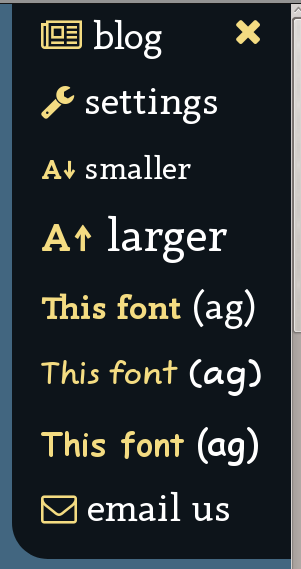
Gut lesbare Webschriften
Hallo, gibt es irgendwo einen guten Artikel über die Lesbarkeit von Webschriften?
Leider hat man ja nicht alle auf dem Markt existierenden Bildschirme und Geräte zum Testen zu Hause.
Ich gestalte gerade die Webseite für eine Organisation für neurologisch Erkrankte (mache sonst nur Print). Open Sans wäre jetzt meine Wahl. Source Sans sah z. B. auf einem niedrig-auflösenden Monitor grauenhaft aus ...
Ist dieser kleine Schalter zum benuzerdefinierten Einstellen der Schriftgröße eigentlich noch zu empfehlen (-> A+ | A-), oder ist sowas inzwischen out?
Wenn Leserlichkeit das Hauptkriterium ist (statt, sagen wir mal, die möglichst stringente Einhaltung eines CD/CI) würde ich überhaupt davon abraten, dem Leser eine Webschrift (ohne einfache Wechselmöglichkeit) aufzuzwingen. Warum? Weil eine Systemschrift seines Systems mit einiger Wahrscheinlichkeit besser leserlich ist (weil eben auf sein System optimiert) als irgendein Webfont.
Was macht ein Smartphonebesitzer denn als erstes? Richtig: eine Schrift aussuchen, die ihm gefällt/die er auf diesem Gerät gut lesen kann.
Webschriften sind ein nettes Extra, aber ich würde sie für besonders sensible Gruppen, was Leserlichkeit angeht, immer nur als Option anbieten. Ich habe in letzter Zeit einiges für Grundschüler gestaltet – in enger Abstimmung mit ihren Lehrern – und da auch mehrere Schriftoptionen angeboten. Das kann sinnvoll und hilfreich sein, weil Systemschriften eben nicht immer optimale Leserlichkeit für besonders sensible Gruppen von Lesern (wie eben Leselernanfänger, Dyslexiker,  Einwanderer, die gerade erst Sprache und Alphabet lernen, Menschen mit allerlei Behinderungen und und und) bieten. Serifenschriften können da helfen, wie auch komplexe a- und g-Formen (die weniger leicht mit o und 9 verwechselt werden) oder besonders humanistisch/»organisch« gestaltete Schriften, bei denen sich b, d, p und q besonders klar voneinander unterscheiden (auch wenn sie gedreht und gespiegelt werden).
Aber auf manchen Geräten sieht dann auch die sorgfältigst getestete Schrift eben nicht so klar aus wie eine Systemschrift. Deshalb: Wahlmöglichkeit!
Schon innerhalb eines Schulbezirks gibt es aber die unterschiedlichsten Geräte, auf denen Schriften ganz unterschiedlich dargestellt werden: ältere PCs, neue PCs, Chromebooks, »richtige« Laptops, Tablets verschiedenerer Generationen, Telefone, Smartboards (auf denen Schriften dann ganz anders wirken als auf dem angeschlossenen PC) . Da ist der Testaufwand schon bei einem Nutzer, den man kennt, enorm. Wenn der Leser irgendjemand sein kann, nun ja …
Nach meinen Erfahrungen ist er (wenn Erwägungen wie die obigen wichtig sind) wichtiger denn je, da eben immer mehr Inhalte auf nichttraditionellen Geräten konsumiert werden. In einem PC-/Laptop-Browser kann ich selbst als naiver Nutzer die Schriftgröße ziemlich einfach anpassen, ohne das Layout zu zerschießen. Ctrl-+ gedrückt oder auf das + in der Browserleiste geklickt, schon ist die Schrift größer! Aber schon auf einem Smartphone ist das klar schwieriger. Klar, da kann ich pinch-zoomen, aber dann passt eben eine Textzeile nicht mehr in den Viewport. Doof! Da kann eine A+ A- Option sehr helfen.
Sehr guter Text, Thorsten! Was man vielleicht auch noch mit einbeziehen könne ist, das viele Browser inzwischen ja einen „Lese-Modus“ haben in dem dann nur der Text der Seite unabhängig vom Seiten-CSS angezeigt wird. Man sollte die Seite auslösen auch so gestalten, das dieser Modus zuverlässig funktioniert.
Und vielleicht wäre es auch schlau, einen Dark-Mode anzubieten.
Schriften würde ich auch nicht fest vorgeben, die Nutzer wissen besser, was ihnen hilft. Ansonsten ist noch eine klare, einfache Gliederung, genügend Weißraum und ein großzügiger Zeilenabstand hilfreich.
Oh, und eine einfache, klare Sprache (nicht unbedingt sofort leichte Sprache, aber in die Richtung halt).
Ansonsten hilft noch eine Präzisierung der "neurologischen Erkrankung", denn Neurologie ist ein verdammt weites Feld.
Ein moderater Dark-Mode ist bei unseren meisten Projekten mittlerweile Standard. Für Traditionalisten gibt’s dann einen Light-Mode.
:-?iPhone-User sind hier wohl nicht gemeint ...
[ironie] Das ist wieder die Erfahrung aus dem First Level Support :shock:
Sorry, wollte nicht pöbeln, die Tipps von euch sind alle goldwert :nicken::trost:
Wollte eigentlich sagen, das die Nutzer für sich Anzeigemodalitäten entwickelt haben können, mit denen sie einigermaßen klar kommen. Das ersetzt natürlich keine begründete Alternative, doch solange wir nicht wissen, wohin optimiert werden soll, können wir auch nur raten.
Erstmal danke für Eure Ratschläge - speziell Dein ausführlicher, Þorsten!
Es geht um die Erkrankung ME/CFS (Chronisches Fatigue Syndrom), Betroffene haben ein Problem mit der Reizverarbeitung, z. B. Licht oder Geräusche. Daher habe ich an den Darkmode auch gedacht.
Hier verwenden wir Myriad. Wie würdet ihr die (oder alternativ Frutiger) für Webseiten-Texte einschätzen? Habe ich im Web noch nicht oft gesehen.
Aber da ist mir das Branding auch nicht so wichtig wie eine gute Konsumierbarkeit. Ich fände es nicht schlimm, wenn wir für Print und Web unterschiedliche Mengentext-Schriften haben, Logo und Farben reichen für die CI.